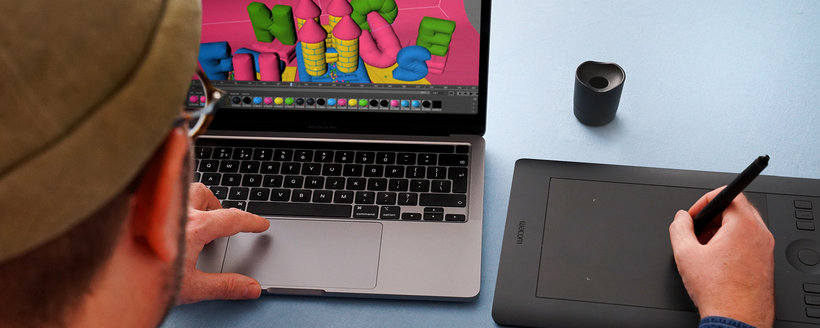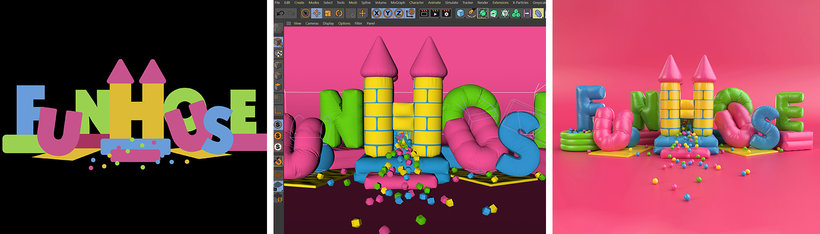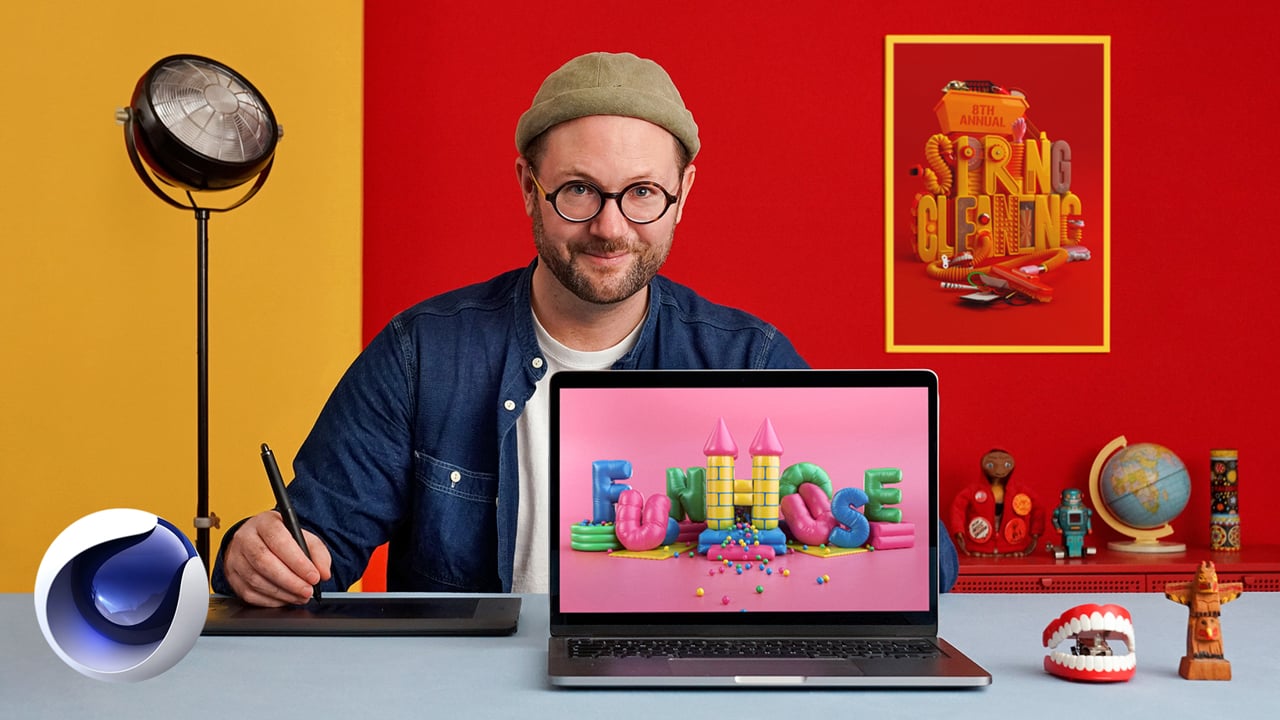
Tipografia 3D: brinque com cores e volume
Um curso de Thomas Burden , Ilustrador 3D
Aprenda a criar animações tipográficas divertidas com Cinema 4D e Redshift
Influenciado pelos brinquedos que ele nunca pôde ter na infância, Thomas Burden cria obras coloridas em 3D que são, ao mesmo tempo, hiper-realistas e atemporais. Seu estilo nostálgico e original combina arte 3D e engenhocas lúdicas em animações para grandes marcas internacionais como Nickelodeon, Netflix, Playstation, McDonald's, Bloomingdale's, entre outras.
Neste curso, Thomas guiará você passo a passo para criar animações tipográficas em 3D usando o Adobe Illustrator, Photoshop, Cinema 4D e Redshift. Ele ensinará a mexer em cada software e explicará seu método para criar imagens 3D divertidas e realistas baseadas em brinquedos infláveis. As técnicas apresentadas neste curso servirão como base criativa para futuros projetos 3D.
Qual é o projeto deste curso?
Você criará uma peça tipográfica em 3D, com aspecto de balão, com a palavra "FUNHOUSE" ou uma obra de arte digital realista à sua escolha. As técnicas apresentadas neste curso são ideais para estabelecer uma base criativa para futuros projetos 3D.
Thomas Burden é um ilustrador 3D de Chichester, Reino Unido. Ele é conhecido por suas obras visuais únicas, que combinam tipografia e engenhocas divertidas e realistas em 3D.
Thomas estudou Design Gráfico na Camberwell College of Arts em Londres antes de trabalhar para os melhores estúdios de ilustração como McFaul e I Love Dust. Em 2013, começou a trabalhar como freelancer, produzindo campanhas publicitárias e outros projetos para marcas, festivais de música, gravadoras e editoriais. Sua lista de clientes inclui grandes nomes internacionais como McDonald's, Netflix, Nickelodeon, Playstation, SC Johnson, Bloomingdale's, The Guardian, The Washington Post, The New Yorker, Harpers Collins, entre outros.
Introdução
Influências
O que faremos neste curso?
Ideias e esboços iniciais
Visão geral do fluxo de trabalho de software
Conceitos iniciais e inspiração
Desenhar um layout em IA e exportar caminhos vetoriais
Tudo sobre Cinema 4D
Configurando o documento Cinema 4D
Crie um esboço 3D em C4D
Adicionando iluminação / texturas básicas e uma câmera com Redshift
Modelando as letras 1
Modelando as letras 2
Modelando o U
Modelando a piscina de bolas
Modelando as almofadas
Modelando as esteiras
Modelando o castelo 1
Modelando o castelo 2
Modelando o Castelo 3
Toques finais: Adicionando dinâmica de pano às cortinas e algumas bolas à cena 1
Toques finais: Adicionando dinâmica de pano às cortinas e algumas bolas à cena 2
Informações extras sobre versões mais recentes do Cinema4D
Toques finais para a imagem final
Ajustando a iluminação / Refinando as configurações de renderização
Usando o Redshift AOV Manager
Importando renderização final e AOV para o Photoshop: preparando arquivos do Photoshop para edição
Editando / Refinando a imagem final usando os arquivos AOV
Salvando a imagem final como um arquivo cliente amigável do Photoshop
Recursos adicionais
Inflar uma carta individual: prática 1
Inflar uma carta individual: prática 2
Introdução ao Redshift
Projeto final